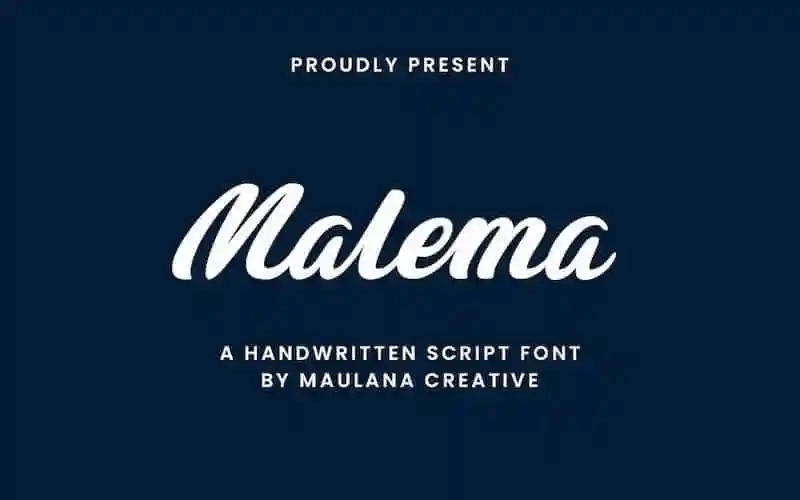
A ‘Malema Handwritten Font’ é uma opção perfeita para aqueles que buscam uma mistura interessante entre o moderno e a literatura orgânica. Desenvolvida pelo designer Hamilton, esta fonte escrita à mão apresenta um estilo sofisticado e único, ideal para criar letra manuscrita fluente. Perfeita tanto para designers digitais quanto para profissionais de design gráfico que buscam dar um toque autêntico às suas criações. Os fonts do tipo ‘Addictive’, projetados para serem uma combinação poderosa, prometem deixar sua identidade visual única e impressionante. A ‘Malema Handwritten Font’ é a escolha perfeita para personalizar qualquer projeto, seja em logotipos, materiais de publicidade ou design editorial, garantindo que seu trabalho fique ainda mais memorável.